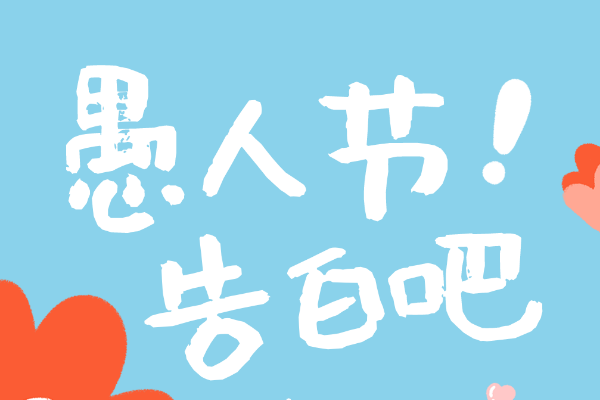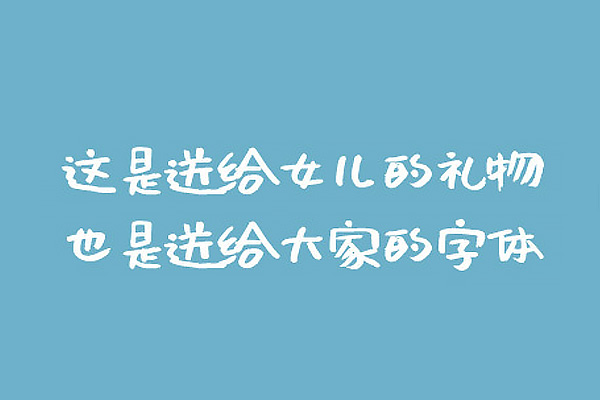
沐瑶软笔手写体
作者是春颜秋色,一位来自重庆的平面设计师。在工作中,经常需要手写文字,但作者发现可用的字体大多比较传统,如楷隶行草等,而一些轻松可爱的字体并不多见。另外,很多好看的字体都存在版权限制,对于设计师来说,使用门槛较高。
为了解决这一问题,作者决定在2018年开始创作一款新的字体。由于作者女儿的生日在七月,作者决定用她的名字拼音来命名这款字体,称之为“MuYao”。作者选择字母命名是为了方便在各类软件中使用,而这款字体实际上是用软头毛笔创作的,因此全名为“沐瑶软笔手写体”。
沐瑶软笔手写体效果预览
沐瑶软笔手写体字体效果预览